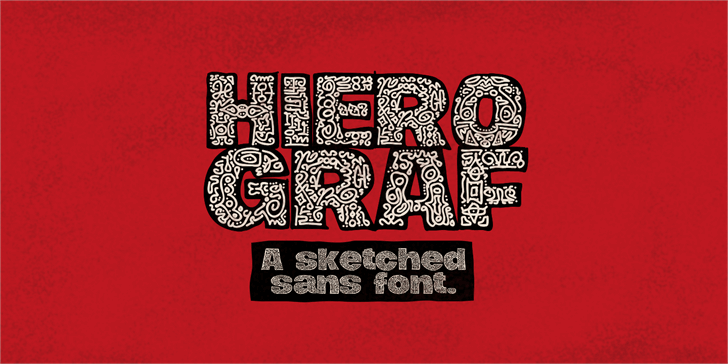
A Hierograf Font é uma tipografia moderna e elegante criada por Hamilton, perfeita para designers que buscam um estilo único para seus projetos. Esta fonte está disponível no gosto do ‘symbol’, com linhas curvas suaves e formas minimalistas. A sua designera Hamilton sabiamente equilibraram estes elementos de forma a criar uma fonte extremamente versátil, adequada tanto para gráficos digitais quanto para impressão. Adaptable e flexível, ela pode ser usada em diversos formatos para atender às necessidades específicas dos projetos. Seja em design editorial, logotipia ou aplicação web, a Hierograf Font oferece uma solução perfeita para qualquer designer que busca algo único e moderno. Se você está procurando por uma fonte de alto nível com um design icônico, então a Hierograf Font pode ser a escolha certa. Comprar uma licença comercial da Hierograf Font é fácil, visite o site oficial da MansGreback.com.